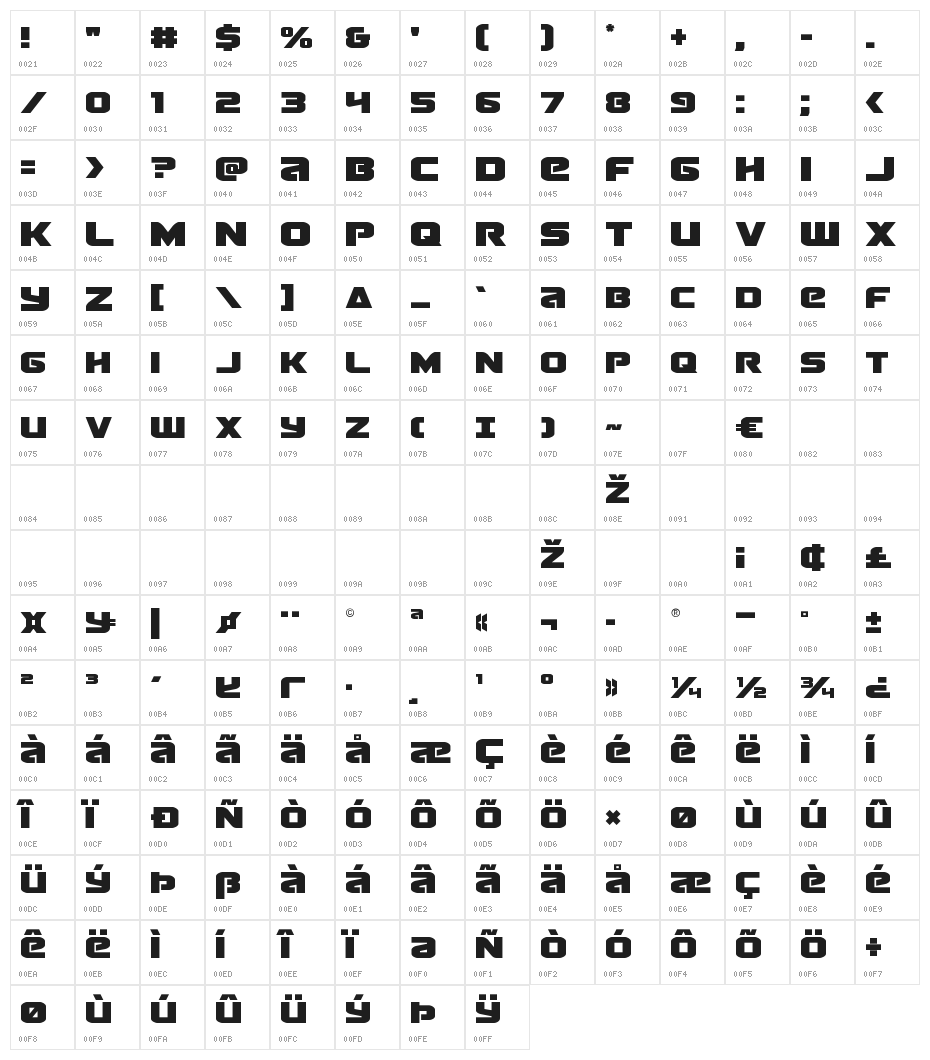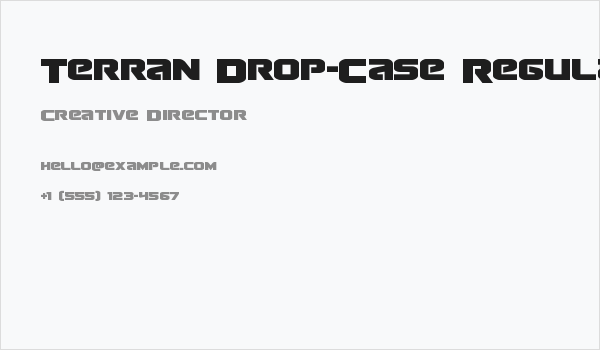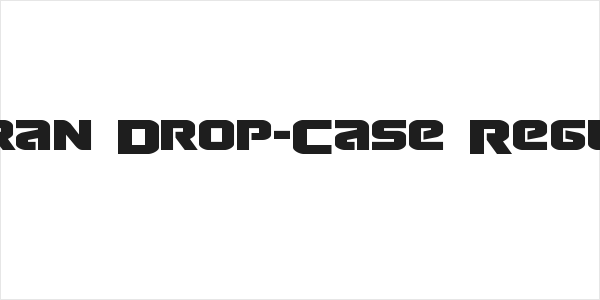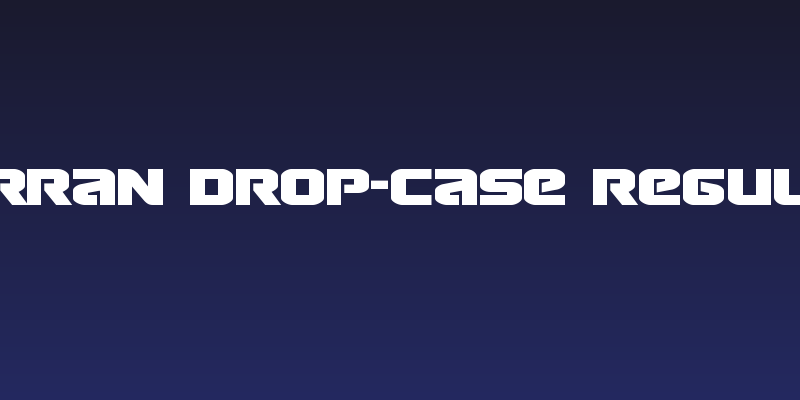
Terran Drop-Case Regular Font
| Progetti proposti | Ideal for sci-fi themed designs, video game titles, technology branding, and modern posters. |
Terran Drop-Case Regular